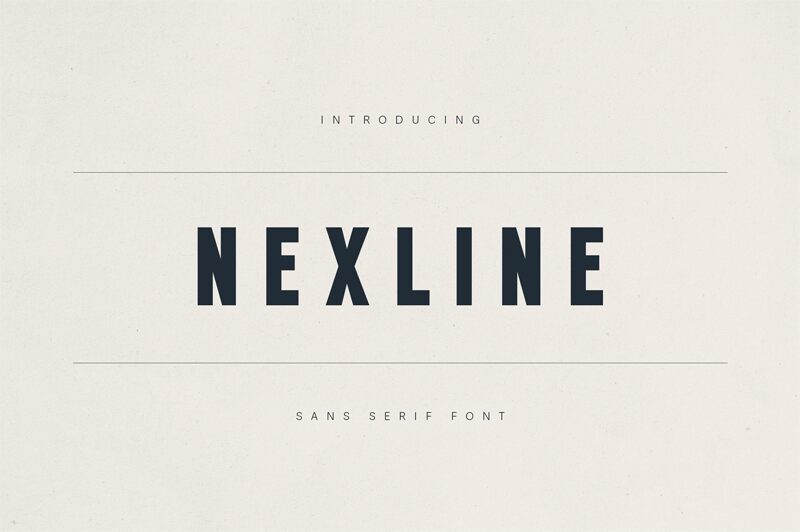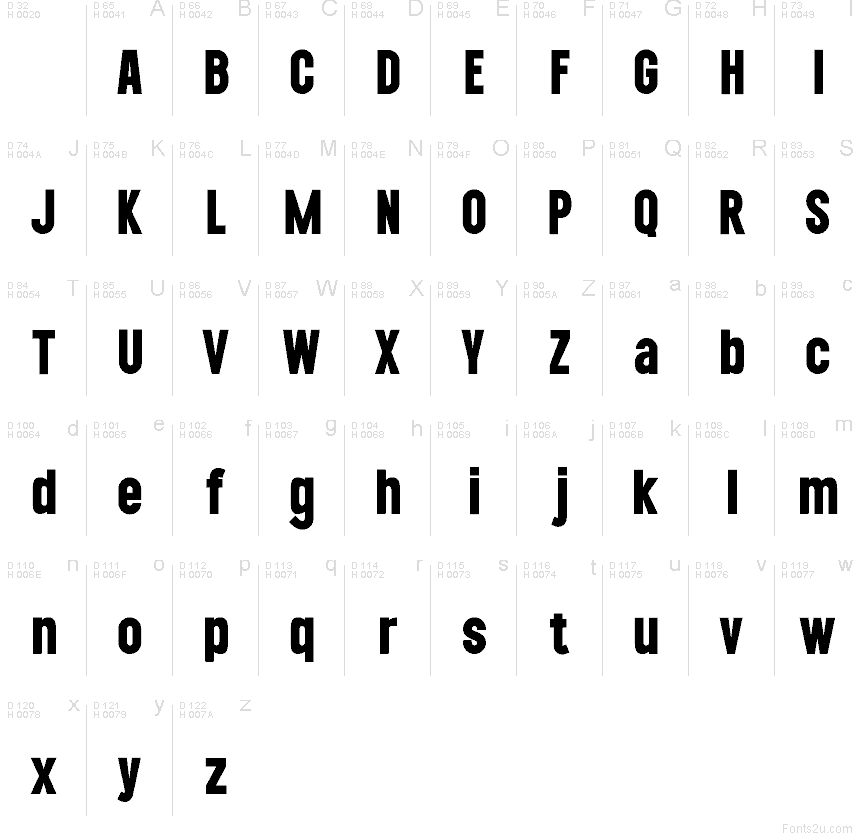
Die Schrift Nexline ist eine kostenlose serifenlose Schriftart mit einer hohen, kompakten Form und präzisen geometrischen Kurven. Ihre abgerundeten Innenräume und geraden Seitenlinien verleihen ihr einen simplen, technisch inspirierten Rhythmus, der beständig wirkt, ohne dabei starr zu sein.
Nexline ist ein kostenloser Font, der ideal für Logos, kurze Überschriften, Plakate, Verpackungsdesign und Sportgrafiken geeignet ist, da seine schmale Struktur für ein direktes und kompaktes Schriftbild sorgt. Er eignet sich zudem hervorragend für App-Beschriftungen, Werbebanner und ausdrucksstarke redaktionelle Akzente, wenn Sie eine schlichte, serifenlose Schrift suchen, die mit einer starken, aufrechten Präsenz überzeugt.